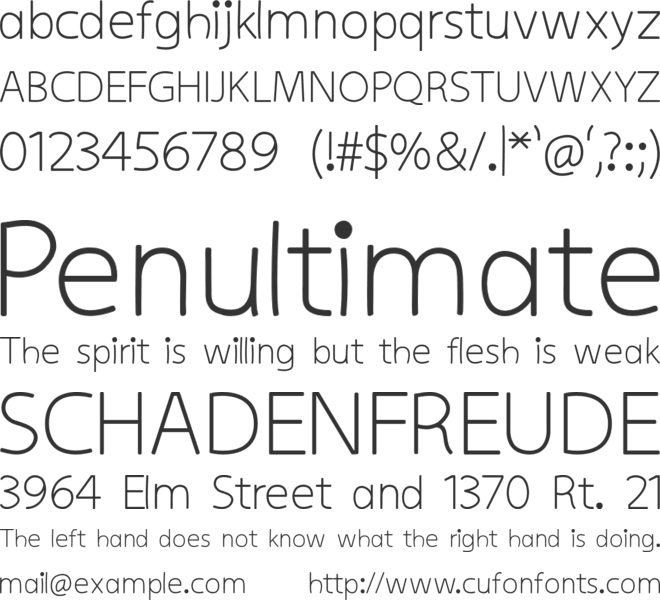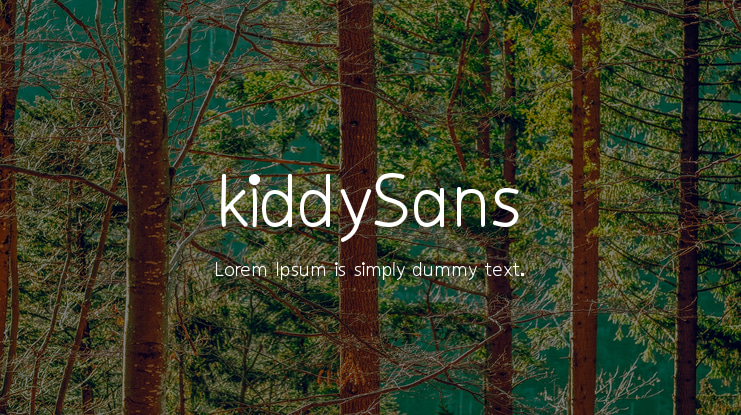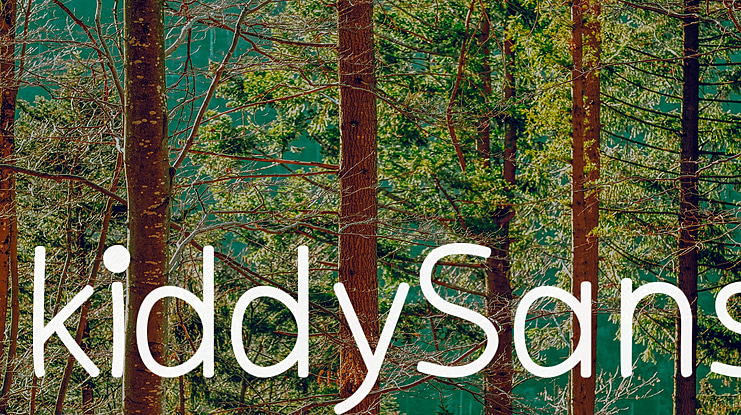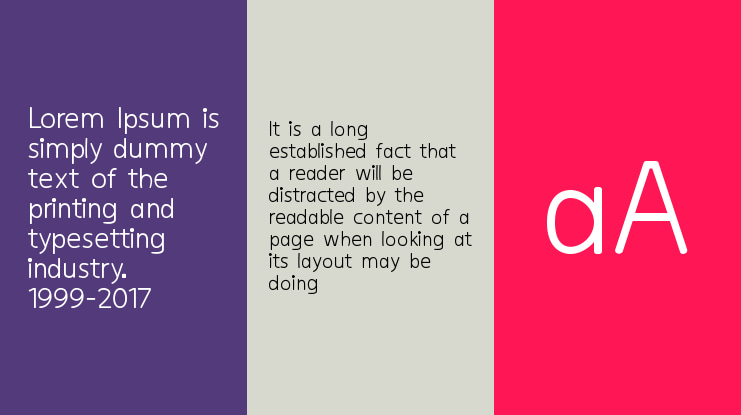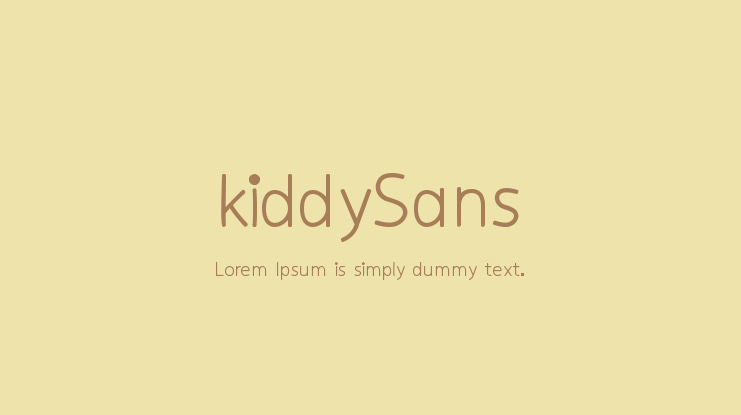
kiddySans Font Family
Head­line Font / Dis­play Font / Sans Serif Font »kiddy Sans« with 8 stlyes & 366 gly­phs, inkl. accents & â¬
IDEE Wie sieht eine kind­li­che, naive Schrift aus, wel­che nicht lang­wei­lig sta­tisch wirkt, genug Persönlichkeit/Charakter hat und den­noch gut les­bar ist?
BESONDERHEITEN Cha­rak­ter­starke Display/ Head­line Schrift
⺠Ãber­groÃe Punkte ⺠Leicht gebo­gene, warme und freund­li­che Stri­che ⺠Offene, freund­li­che For­men ⺠Orga­ni­sche, leicht ver­beulte Formen